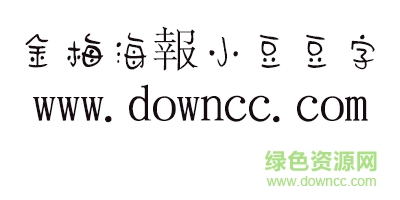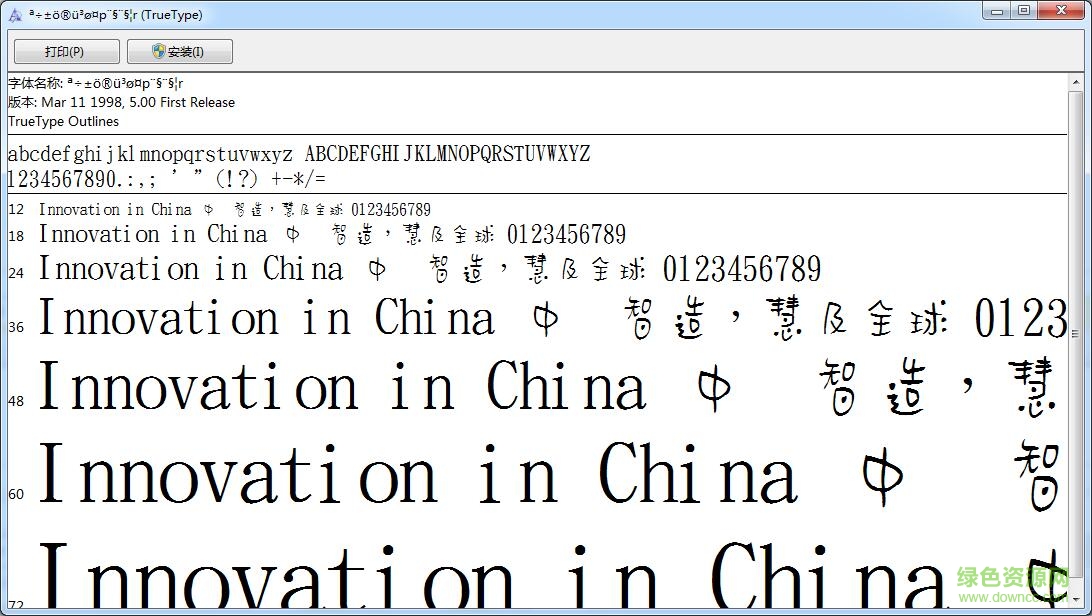
金梅海報小豆豆字字體是金梅字體庫推出的免費字體。金梅海報小豆豆字體字形偏向于卡通,字體風(fēng)格生動活潑。在設(shè)計行業(yè)很受用!需要的用戶快來下載安裝吧。
金梅海報小豆豆字是金梅字體庫中的一款應(yīng)用于設(shè)計方面的字體,該字體飄逸大方,帶有小豆豆形狀,可以應(yīng)用于名片設(shè)計、平面設(shè)計、廣告設(shè)計、報紙雜志等領(lǐng)域!歡迎大家來綠色資源網(wǎng)下載使用。